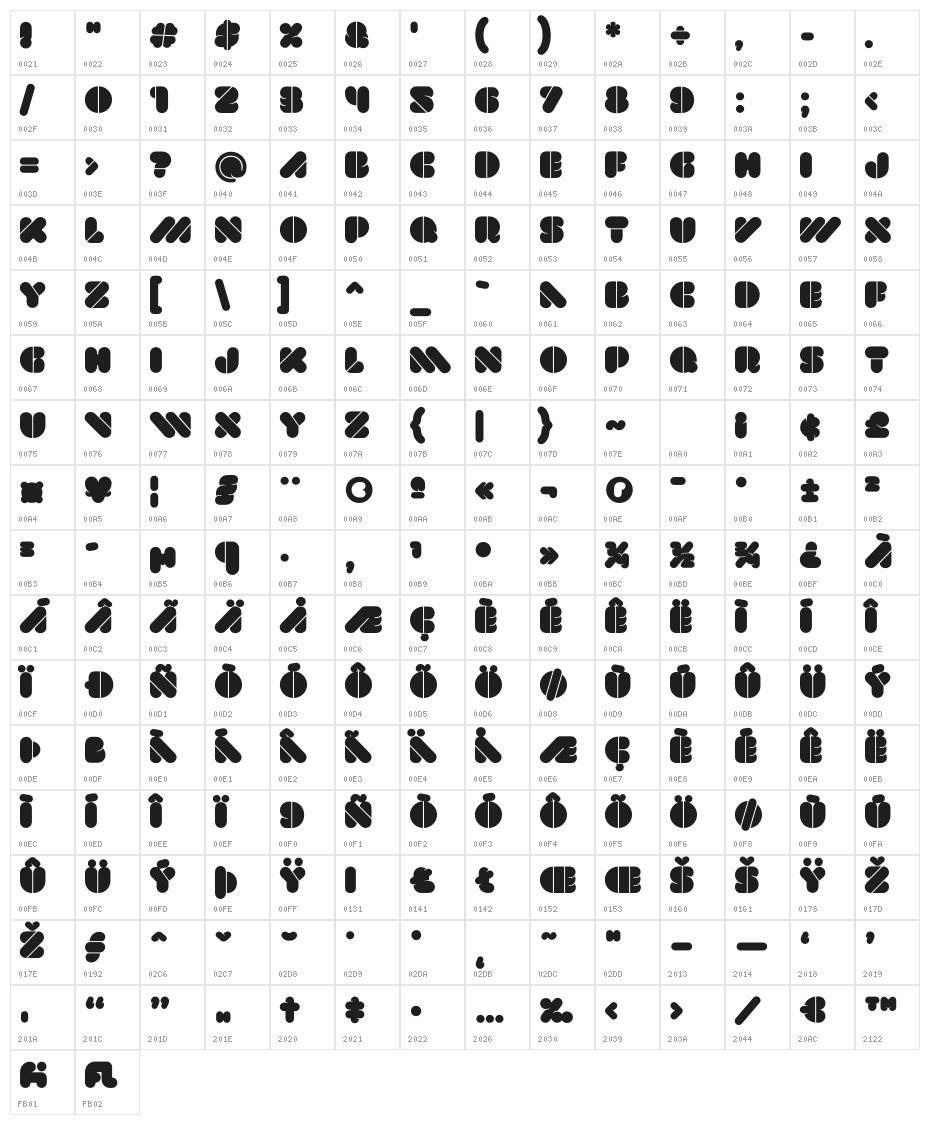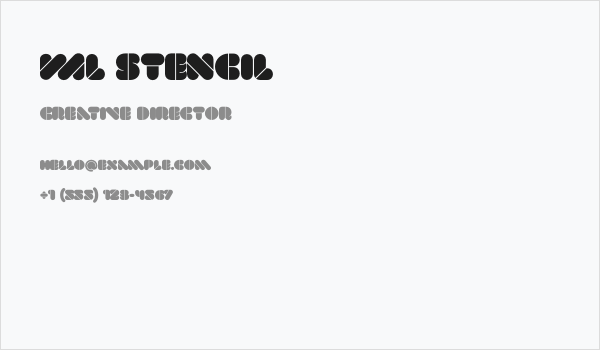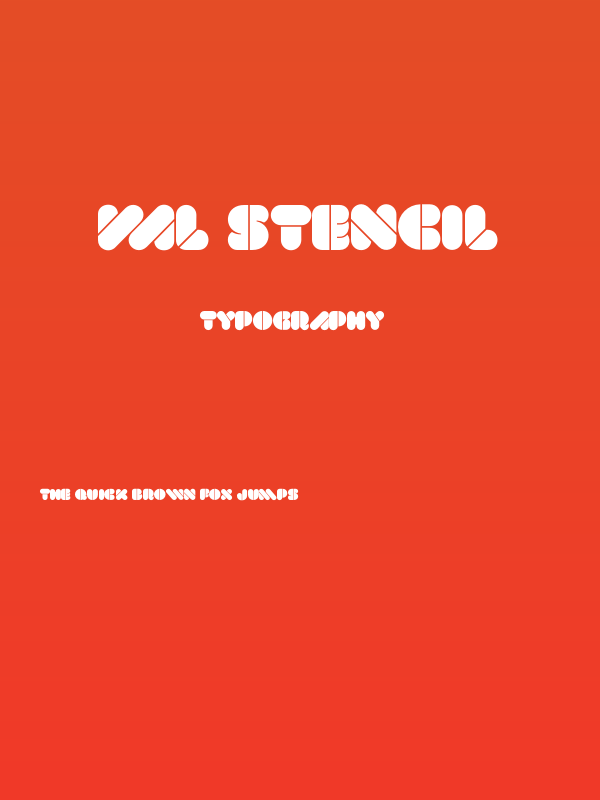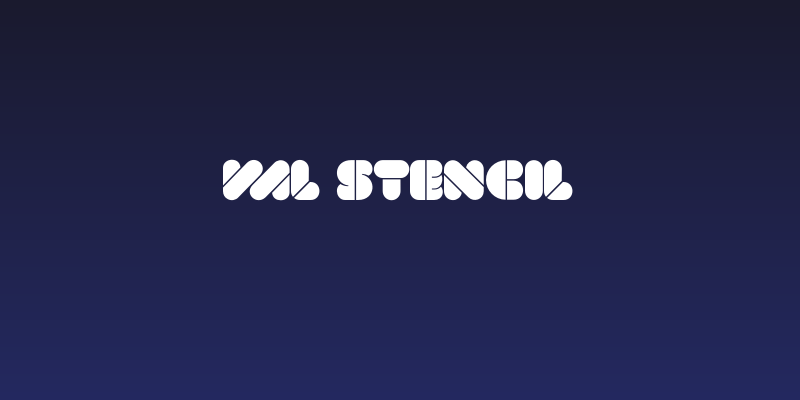
VAL Stencil Font
| Область применения | Logos, Headlines, Posters |
| Рекомендуемые проекты | Ideal for branding, posters, signage, and any project requiring a modern, industrial look. |
VAL Stencil